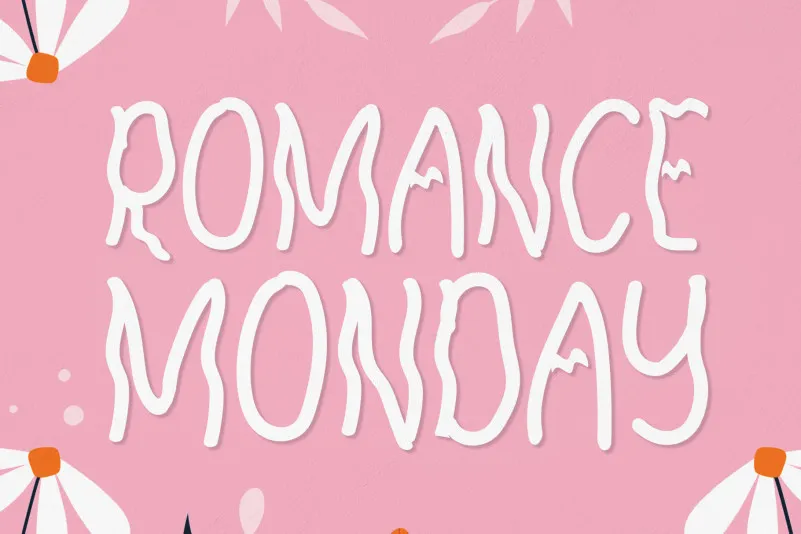
Romance Monday Display Font – Download Grátis
Romance Monday Display Font é uma tipografia desenhada à mão com um toque único e intrigante. Seja para nomes de empresas, selos ou qualquer projeto de identidade visual que deseje destacar, esta fonte traz a elegância de um estilo livre ao seu design. Adoptando as características de uma escrita à mão autêntica mas com a força de uma fonte de exibição, você pode adicionar profundidade e personalidade aos seus projetos. Este é o tipo de fonte que destaca sua presença nas páginas web ou impressas, tornando-os ainda mais chamativos. Especialmente recomendada para designers de logos e selos, esta fonte oferece uma combinação perfeita de originalidade e versatilidade. E embora seja baseada em estilos manuscritos, ela também pode ser usada em situações que exigem um toque mais formal ou elegante.